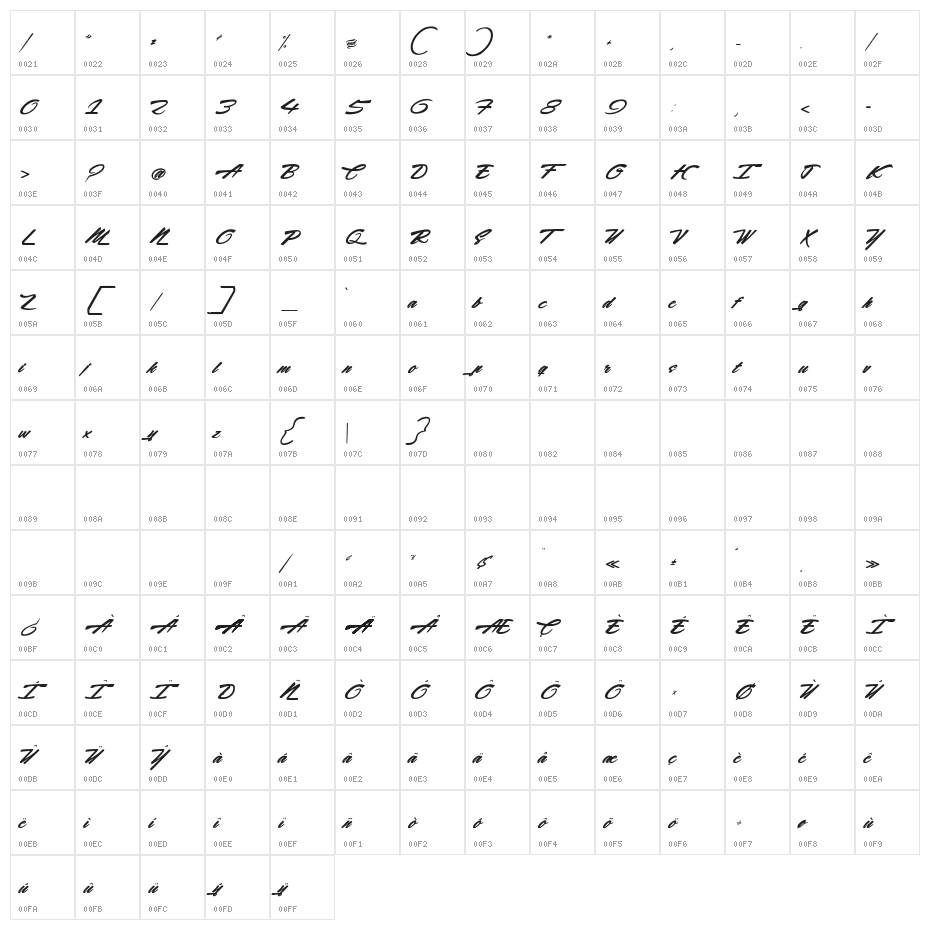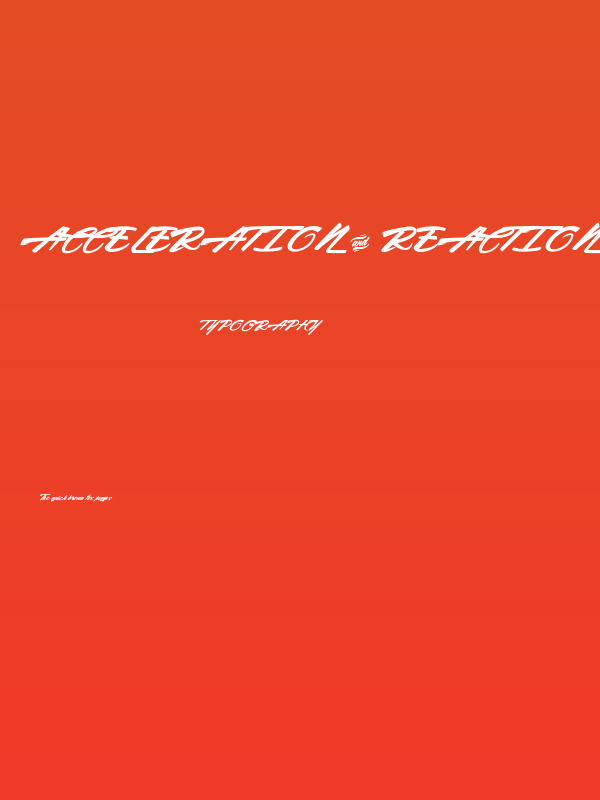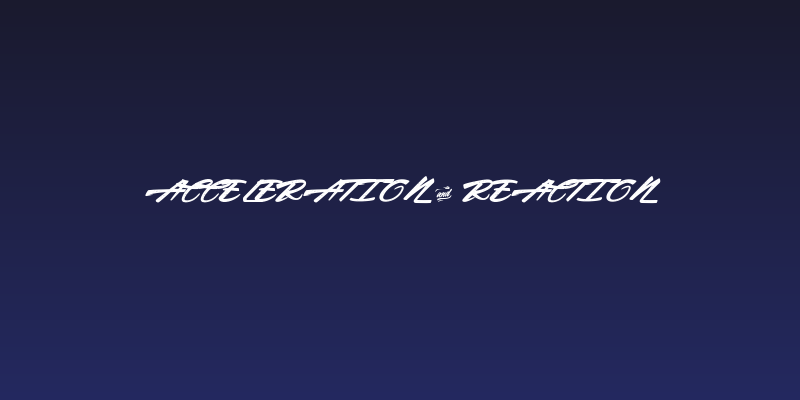
Acceleration & Reaction Font
✎ Script
| Anwendungsfall | Logos, Invitations, Branding |
| Vorgeschlagene Projekte | Ideal for branding, logos, invitations, and any design requiring a touch of elegance and motion. |